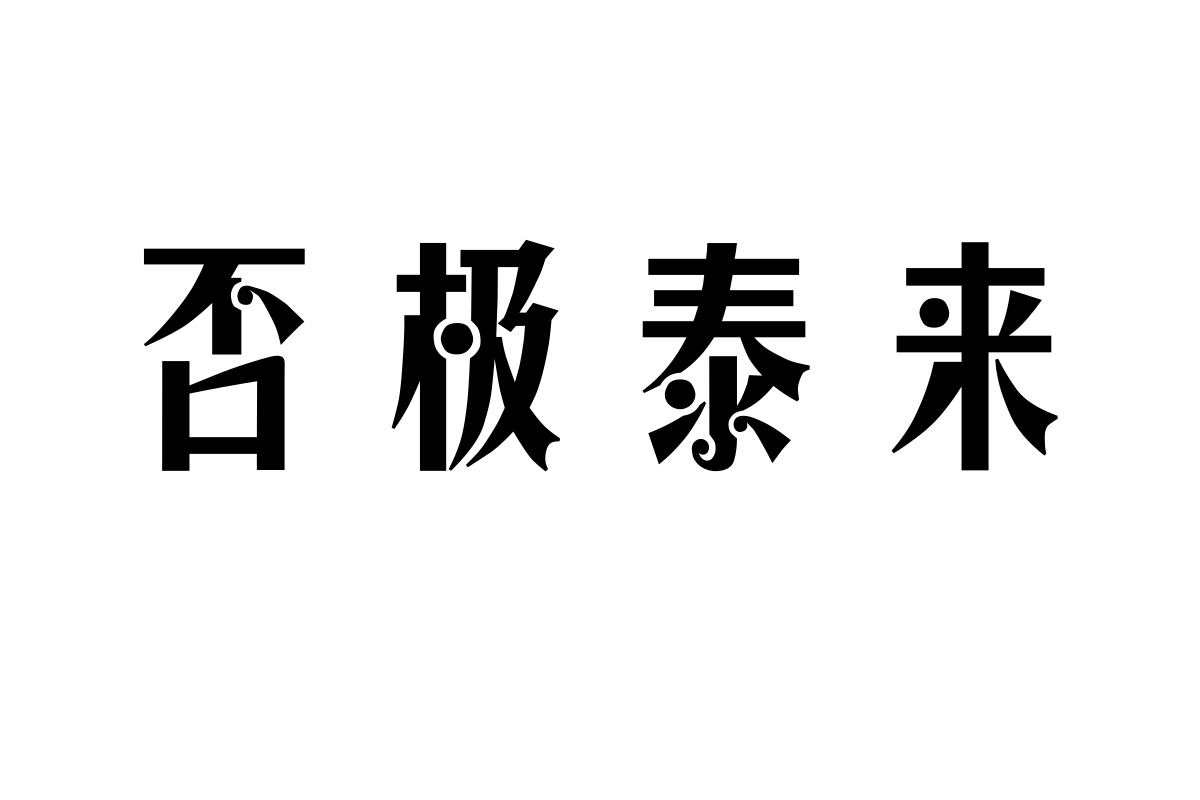
汉仪长艺体简是一款由汉仪公司推出的字体,具有简洁、优雅的特点。这款字体采用了现代的设计理念,将传统的书法元素与现代设计相结合,使得字体既有古典韵味,又不失现代感。
汉仪长艺体简的笔画流畅,结构紧凑,字形大小适中,易于阅读和书写。它的线条粗细适中,既不过于粗犷,也不过于细弱,给人一种舒适的感觉。同时,该字体的字形也具有一定的艺术性,线条起伏有致,富有节奏感,使得整体视觉效果更加优美。
此外,汉仪长艺体简还注重细节的处理,如字间距、行间距等都经过精心调整,使得整个字体看起来更加协调统一。同时,该字体还具有良好的可读性,无论是在印刷品上还是电子屏幕上,都能保证清晰易辨。
总的来说,汉仪长艺体简是一款非常实用的字体,适合用于各种需要展示文字美感的场景。无论是用于书籍、杂志、广告还是网页设计,都能展现出独特的魅力。